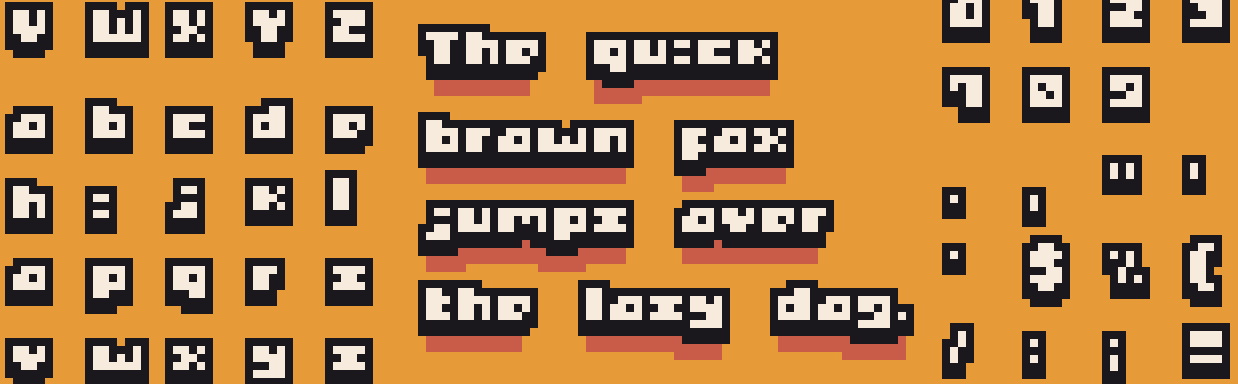
Новый шрифт «bitByBit_» для вашей игры
Разработчиком analogStudios_ нарисован и выложен для свободного скачивания новый англоязычный шрифт в пиксельном ретро-стиле «bitByBit_», который вы можете использовать по лицензии CC-0 в вашей игре.
Обратите внимание. Что этот шрифт был создан для проекта, в котором используются только прописные буквы... поэтому некоторые строчные буквы труднее читать (a, e, s и z, в частности).
TLTВыпущена версия 1.1 уже. Добавлены версии шрифта Outlined 1 и Outlined 2, а также несколько новых символов и сделаны некоторые доработки.